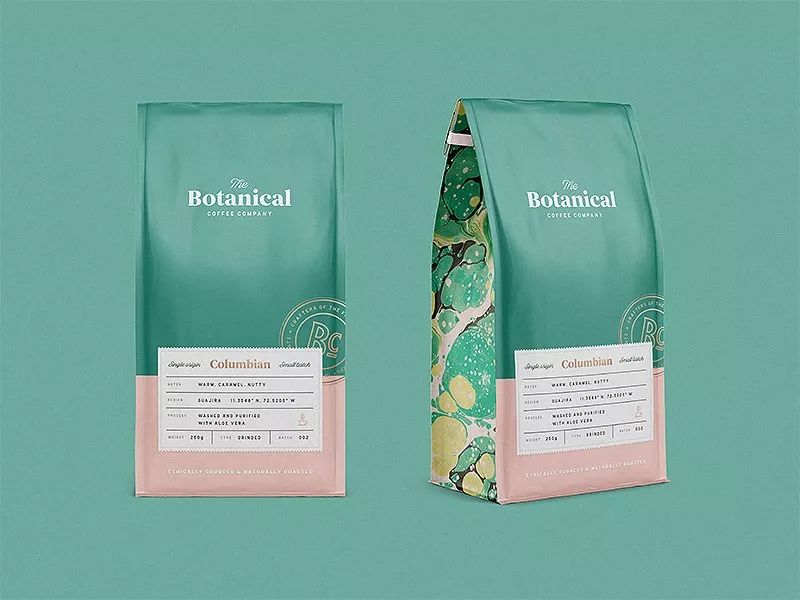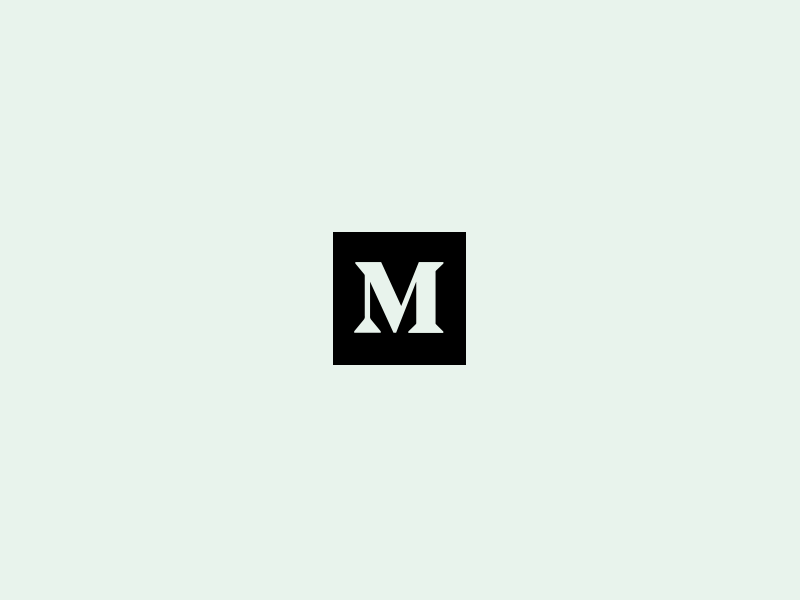
这是我看过最详尽的2019设计趋势,来自Dribbble
为什么去取N个设计流行趋势?因为我写的更多是2018年追波一整年最流行的设计作品。再则每个设计师自己的定位不同,职业技能不同,喜欢关注的领域不同,大家会自己判断哪些流行趋势适合自己并会花时间钻研进去。
我筛选整理了追波2018一整年最流行的设计作品,共578个作品,578个作品中每个作品点赞数都过千,通过提炼每个作品元素中的共通性整理了追波N个设计流行趋势。
品牌升级
By Medium
Medium 是一个轻量级内容发行的平台,允许单一用户或多人协作,将自己创作的内容以主题的形式结集为专辑,分享给用户进行消费和阅读。
2017年8月21日,Medium对自己品牌识别进行全面升级,有原来具有可塑性的折叠式“M”直接改成了衬线字母,这次调整中没有保留原来的任何设计元素,把两年辛苦建立的品牌基因完全丢弃。但是它在产品用户体现下足了功夫。
Medium强调用视觉化的图文样式提高用户的阅读体验、用主题为核心的内容组织方式来聚合内容、用用户投票的众包形式进一步精选内容、用精美的网站模版来加强页面的结构化。对 Medium 这样的新的内容发行形式来说,作者、品牌不是最重要的,话题才是核心。Medium 不希望用户仅仅因为某篇文章是某个作者所写就去阅读,而希望他们阅读的理由是因为该文章的话题是其真正关注的。目前很多国内设计类的译文都来自Medium这个平台,我也会每天关注这个平台,里面的热点设计类文章很具有前瞻性和实用性。
品牌调性
By green chameleon
品牌调性,是基于品牌的外在表现而形成的市场印象,从品牌人格化的模式来说,等同于人的性格。Botanical采用衬线字体突出咖啡个性品牌调性,品牌色绿色代表纯天然,贴近自然,很阳光。淡淡的暖红色辅助色拉回了天然健康同时还兼顾女性客户喝Botanical咖啡。整体包装也采用细细的字体,Botanical衬线字体正负形比重和字母之间的间距都恰到好处。
欧美风
By Nick Slater
欧美风的logo主要以简洁紧凑为主,英文字母的构成基本上都是线条路径环绕,图形也是通过高度抽象提取造型,通过处理后所形成的文字和图形相对简单整齐,容易与其他颜色或者背景形成统一的效果,突出重点,可以给人很深刻的印象,同时也容易记忆。很多NBA球队的logo风格都是类似这种欧美风格。
品牌延展
By Eddie Lobanovskiy
为了获得更有效的传递品牌价值,需要建立包括Logo、配色、字体、图标等一整套视觉规范,还需设计元素规范和辅助图形。首先需要确定品牌主色、辅助色。用户在使用现在的多平台互联网产品中,图标是重要的品牌设计元素,可以很好的辅助品牌延展到产品中去,统一的图标设计可以帮助用户更容易识别品牌所传递的价值。
包装设计
By Mike | Creative Mints
商品包装展示的商标、图形、文字和组合排列在一起的一个完整的画面。这四方面的组合构成了包装设计的整体效果。商品设计构图要素商标、图形、文字和色彩的运用得正确、适当、美观,就可称为优秀的设计作品。
包装设计的图形主要指产品的形象和其它辅助装饰形象等。图形作为设计的语言,就是要把形象的内在、外在的构成因素表现出来,以视觉形象的形式把信息传达给消费者。要达以此目的,图形设计的定位准确是非常关键的。定位的过程既是熟悉产品全部内容的过程,其中包括商品的商标、品名的含义及同类产品的现状等诸多因素都要加以熟悉和研究。
界面
三维
By Mike | Creative Mints
随时C4D软件的火热,在界面设计中很多主体元素和造型都采用三维的设计手法,通过简单建模,加材质渲染后进行页面排版,这种手法增加画面质感,烘托气氛。Make大神不但自己手绘能力很强,还尝试通过三维软件对造型、配色、光影进行更深层次的研究。这两种的视觉体验还是有明显的不同之处。
网格规范化
By InVision
网页设计中使用网格系统可以更好的规范网页内容,我们看到,使用网格系统的网页设计,非常的有条理性;看上去也很舒服。最重要的是,它给整个网站的页面结构定义了一个标准。网格系统虽然没有统一的准则,但是设计师可以采用黄金分割0.618、白银比1.414经典比例划分,或垂直间距与网格系统的间距相同或是整倍。网格系统的参数根据项目的实际情况,尽量建立10的倍数或8的倍数。
极简风
极简风格的界面设计通常要具备几个特征:简洁、清晰、一致,并且可用。你的交互体系应当通过清晰的视觉传达方式帮用户定位并解决问题。可以通过简单的配色方案;可使用大字体和醒目的色彩来让特定的数据成为视觉焦点;也可以大胆使用留白让画面具有呼吸感。
暗调高亮风格
By Eddie Lobanovskiy
暗调高亮风格是一种新兴的艺术风格,近年来在网页设计中广泛应用。暗调高亮风格会更具个性化,也被广泛年轻人所接受。暗调高亮风格一般以黑色或深色调为背景色,加上一种高饱和度、高亮度的颜色作为主色,首页过多亮色搭配不好会影响网页的视觉效果。暗调高亮风格对背景颜色光影明暗处理得当就显得十分重要。
形式感
By Mike | Creative Mints
腾讯设计师晋小彦出过一本书《形式感+:网页视觉设计创意拓展与快速表现》,里面写了很多一些关于形式感设计方法论,比如抄现实的三步骤:减法、分块、加法,把现实事物提取形态,然后把信息内容与形态结合排版形成一个整体,让画面更形象生动有趣。界面中把一幅插画拆分到每一个小的分块,通过打散方块让画面更有趣,增加美感的同时也增加画面的动感。
动效
品牌动效
By Unfold
By lgor Pavlinski
品牌动效Logo作为一种更新颖的展现方式,动态图形会更容易被用户所理解,也具有更高的品牌辨识度。给人更加愉悦的视觉享受。一个好的有趣的动态Logo能够让人触发不同的情感。我们在设计时可以营造一个美好的故事情节,也可以体现我们品牌Logo设计中专业度为创新点。在品牌设计上有所创新,让用户更加认可该公司的专业性。
界面微交互动效
By Magic Unicorn
By Google
界面微交互动效会让用户体验更加精致到位。想要打造优秀的产品设计,微交互和动效设计是绕不开的,UI界面设计通过微交互反馈告知用户当前正在发生的事情,所处的状态。Google系统中控件规范化会让界面更规范化。细微的动效更能调动用户情绪,取悦用户。
插画动效
By Markus Magnusson
By Zak Steele-Eklund
插画绘制一般都具有艺术感,插画传达的信息是否明确就显得格外重要。适当添加简单的动效,会增加插画的场景性给用户带入感。插画和动效结合起来更容易引导用户,吸引人的眼球。插画动画可以帮助用户更好的了解内容,会让用户在界面插画中寻找可交互的体验乐趣。
Mg动画
By Markus Magnusson
Mg动画需要很好的节奏感、韵律,每一个场景动画都需要其中的元素进行连接变化,让转场动画更加自然,Markus Magnusson动画通过点线面的动效变化让画面更加有趣、自然,会让人更加印象深刻。
弹性动画
By Markus Magnusson
By Gal Shir
By Eduard Mykhailov
Q弹动画中的Q弹效果会让画面更加有趣,会让人重复欣赏不回感到腻。使用AE弹性表达式Bounce 和 Overshoot!利用这个两个表达式你可以轻而易举地实现各种弹性动画,也可以使用Ae脚本:物体弹簧弹性预设脚本 Aescripts Rubberize It,可以将你的物体图形层中的元素模拟成具有弹簧弹性效果,更符合力学!
人物角色动效
By Eran Mendel
By David Calderon
人物角色动画的AE使用插件较多,Puppet Tools插件利用图钉来制作骨架的工具,但因为图钉工具本身的缺陷,容易破图。DUIK插件现在普遍用在AE制作角色动画(角色动画比较硬),RubberHose插件角色动画比较软,相对更加自然。为了更好的做好人物角色动画还需要平时对人物形态更细致的观察。
酷炫科技风
By Milkinside
AE Trapcode插件最常用的是particular和form了,这两款粒子插件可以制作出很多酷炫的动态效果,随着科技进步上面的动态炫酷风格可适用于多媒体大屏展示或用于公司企业官网,通过粒子插件来突出企业科技感,多用户互联网公司。
三维动效(C4D)
By Gleb Kuznetsov✈
c4d三维场景动画通过构建实物和场景模拟生活中的现实场景,会让用户体验真实感,三维软件制作动效的最大优势是通过动力学和表达式会模拟真实感,未来在AR/VR领域会有更好的发展。相对于界面动效学习成本难度也相对较大。
伪3D旋转动效
By Gal Shir
By Markus Magnusson
伪3D旋转动效渐渐的成为一种趋势,360度无死角旋转对角色造型有更高的要求。伪3D旋转动效也渐渐被更多的设计爱好者所喜欢,伪3D旋转动效主要使用了ae表达式进行制作对360不同旋转角度进行定型,这种动效比较新颖、很有意思百看不厌。
游戏动效
By Mike | Creative Mints
By Markus Magnusson
游戏动效可以很好的引导玩家操作,帮助新手引导,让玩家了解游戏规则和操作使用,好的游戏动效可以增加用户粘性。游戏动态、场景特效、角色动画对动画运动规律都有很高的要求,游戏动态demo也可以节约研发人员的时间成本和沟通效率。
图标
渐变篇
By Ramotion
在扁平化设计刚兴起之时,很多的ICON以纯色和图形为主,然而随着渐变色的流行,当图标使用了渐变色彩,显得更加符合趋势。将渐变的设计同扁平化设计的美学特征融为一体。同样的图标,运用了不用色调的变化都会呈现不同的深度和层次。使用得当的渐变色彩,可以使界面和图标的设计感得到迅速提升。
线面结合
By Eddie Lobanovskiy
线面结合图标是一种很出彩的风格,线是高度概括的图标,这时候面更多的是充当装饰点缀的作用。面的表现方式也有很多种,可以是单色的,渐变色的,也可以像MBE风格那样提取主体结构形成的面,也可以提取图标里面有闭合路径所形成的面。这种风格应用也非常广泛。
拟物风
By Servin
看惯了扁平风,还是觉得拟物风更加精致耐看,追波最早一批UI设计师擅长拟物风格。需要对造型、光影、材质、绘画功底都会要很高的要求。ios为代表的都是过去拟物风格的表现方式,强调的是对单一物件的刻画细节仿真。如果从更广义的范围去讨论,只要与现实世界有所关联,都应该称为拟物?所以当下的设计趋势,便是这种广义上的拟物,越来越强调现实世界的物理特性。
Windows也推出了一套自己的设计语言-Fluent Design System,基于平面化设计上增加了通过光感、阴影、材质增强信息的层次感。模拟物理现实的弹性、光影、阻力等特性。增强了widget或者其他元素的动画特性以此来凸显现信息。整体更加易用、简洁且信息突出。
表情包
By Ryan Putnam
表情包在国内还是有很广阔的市场。表情包这个东西太神奇了,可以使枯燥的文字变得有趣,表情的意义让生硬的文字更有人情味儿,让聊天变得更加有趣。斗图在聊天群或聊天软件很常见,最厉害的那种人可以不用打字就可以和别人聊天,不论别人说什么都有对应的表情回去,而且很恰当,这样的聊天真的让人很开心。表情包的应用还可以解放人的天性,很多常在内心深处不方便表达的都可以用表情包来表达自己的心声。
总结:
2019年自己尝试写第一篇设计流行趋势实在不易,陆陆续续也准备了大半个月,先把追波2018年1000赞的优秀作品下载下来进行分类总结,发现符合当下趋势的设计作品,对单个作品进行分析解刨。从578个作品中第一轮筛选还剩200多个优秀作品,第二轮筛选也还剩128个作品,优秀的作品实在太多了,最后还是在128个作品中刷选出以上N种流行趋势,大家可以根据自己的喜好和实际的工作需要提高相对应的技能。